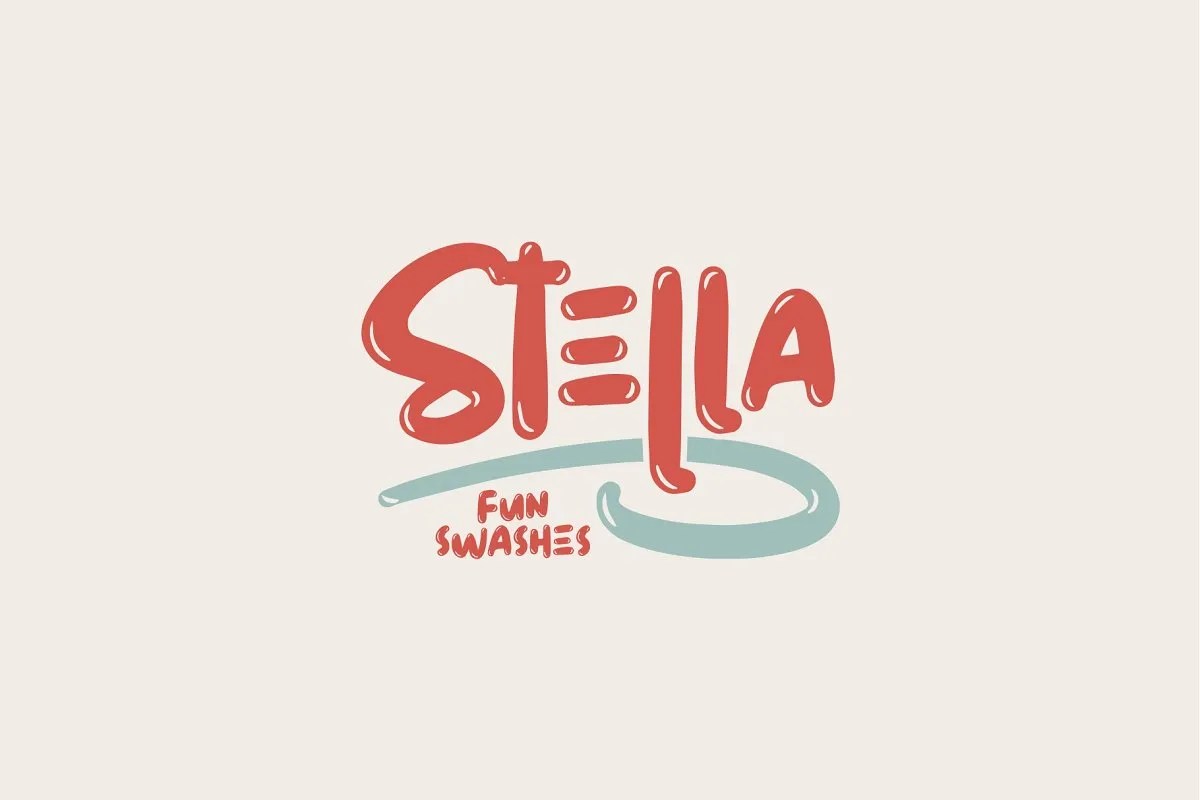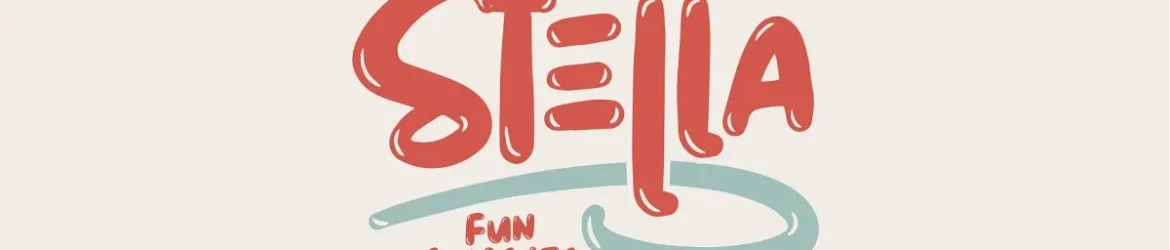
Estamos ansiosos para apresentar Stella Bold Script Font, uma nova adição à nossa categoria de Fonts Script que certamente vai fazer a diferença no seu próximo projeto. Esta fonte é perfeitamente adequada tanto para uso casual quanto para trabalhos mais sérios. Ela se destaca por sua simplicidade e naturalidade, oferecendo um toque casual e descontraído sem perder o poder de impacto. Stella foi criada a partir de um estilo bold e divertido, com várias variações de swashes que adicionam um charme único ao seu design. Com as letras dos dois reinos – maiúsculas e minúsculas – Stella é uma escolha perfeita para qualquer projeto onde você deseja incluir um toque elegante e personalizado. Seja em cartões de aniversário, sites ou até mesmo em artigos publicitários, a Stella Bold Script Font certamente enriquecerá sua experiência gráfica. Não deixe de experimentar essa nova fonte para garantir que suas criações estejam sempre à frente do resto.